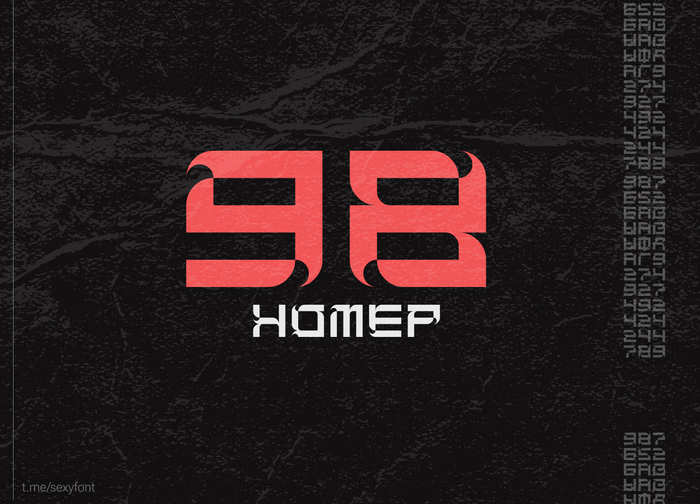
74 Amir74 Авторские презентации шрифтов на кириллице Кириллические шрифты 1 год назад Шрифт blos Бесплатный шрифт с интересными узорами. Особенно в цифрах) Автор: Victor KmitБесплатно для личного и коммерции Скачать в вк | Скачать в телеге со шрифтами [моё] Шрифт Photoshop Дизайн Кириллица Длиннопост Ещё 0